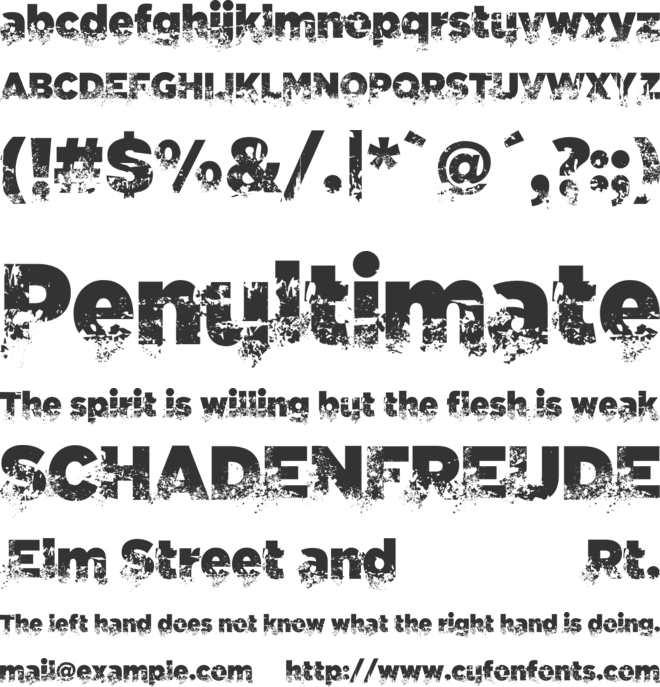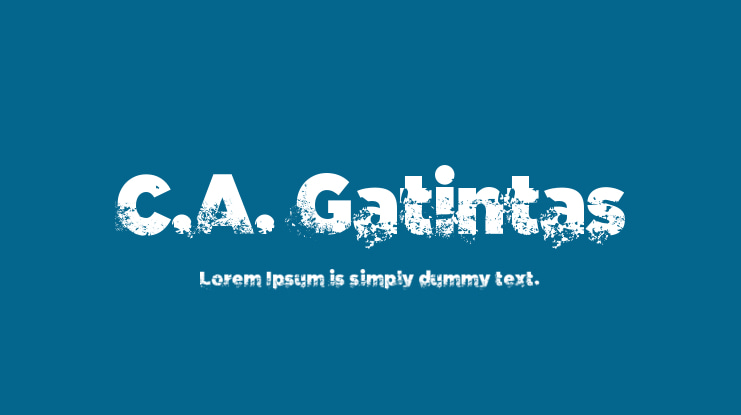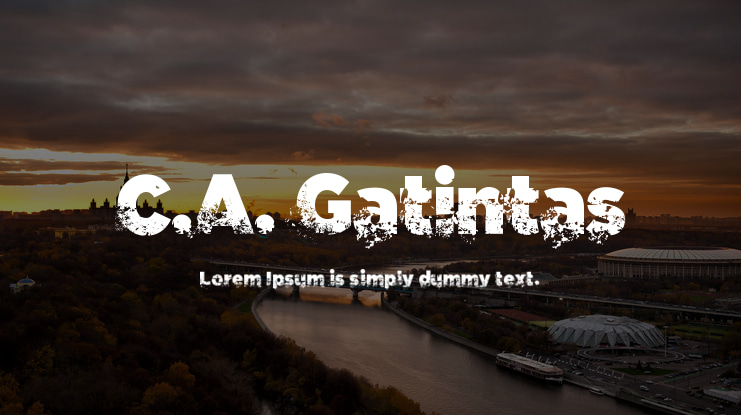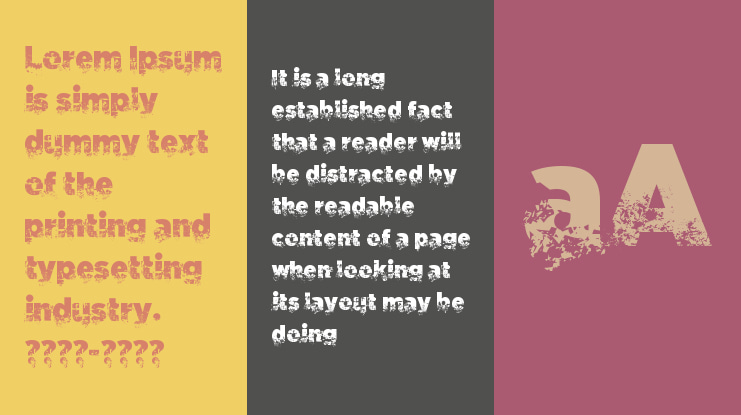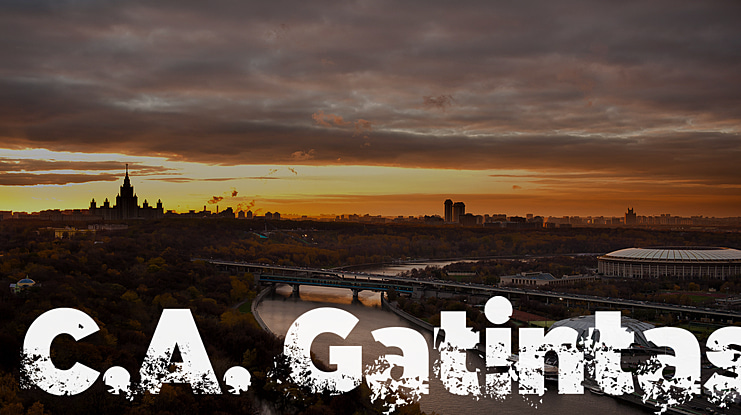
C.A. Gatintas Font
C.A. Gatintas es una fuente sans, experimental, sucia y degradada, realizada en un ejercicio de deconstrucción violento y descuidado, en ella se puede apreciar el paso del tiempo y sus cicatrices, la huella de elementos naturales y otros que no lo son, un sumo proceso de bio degradación tipográfica.